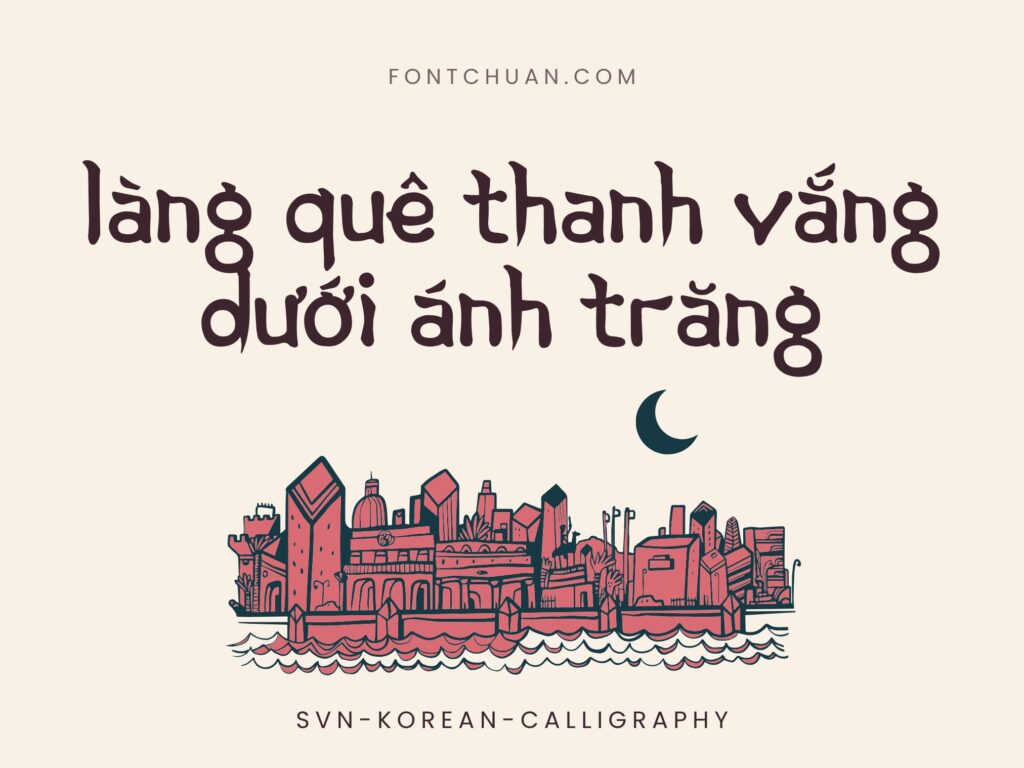
Font SVN Korean Calligraphy Việt Hóa
Font SVN Korean Calligraphy là phiên bản Việt hóa của kiểu chữ Korean Calligraphy, được thực hiện bởi STYLEno.1 Fonts. Font này được lấy cảm hứng từ thư pháp truyền thống Hàn Quốc, với những nét bút lông uyển chuyển, mềm mại, mang đậm dấu ấn Á Đông. Thiết kế của Korean Calligraphy tạo nên phong cách trang trọng, cổ điển nhưng vẫn gần gũi và dễ tiếp cận. Font bao gồm đầy đủ chữ cái, chữ số, dấu câu và hỗ trợ đa ngôn ngữ, phù hợp cho các dự án có chủ đề văn hóa, lễ hội hoặc ứng dụng trong các thiết kế nghệ thuật mang sắc thái phương Đông.
SVN Korean Calligraphy cũng có thể được sử dụng như một Font chữ ẩm thực, giúp các nhà hàng, quán ăn và thương hiệu thực phẩm thể hiện nét tinh tế, sang trọng và gần gũi trên menu, bao bì sản phẩm hoặc các ấn phẩm quảng cáo. Ngoài ra, font vẫn phù hợp với các ứng dụng như tiêu đề sách, thiệp mời, poster sự kiện, bao bì sản phẩm mang yếu tố truyền thống. Các ngành nghề như giáo dục, quảng cáo và ẩm thực có thể tận dụng font này để tạo dấu ấn khác biệt. Font cũng rất thích hợp cho các sự kiện như Tết, Trung thu, Halloween hoặc các dịp lễ hội trong năm.